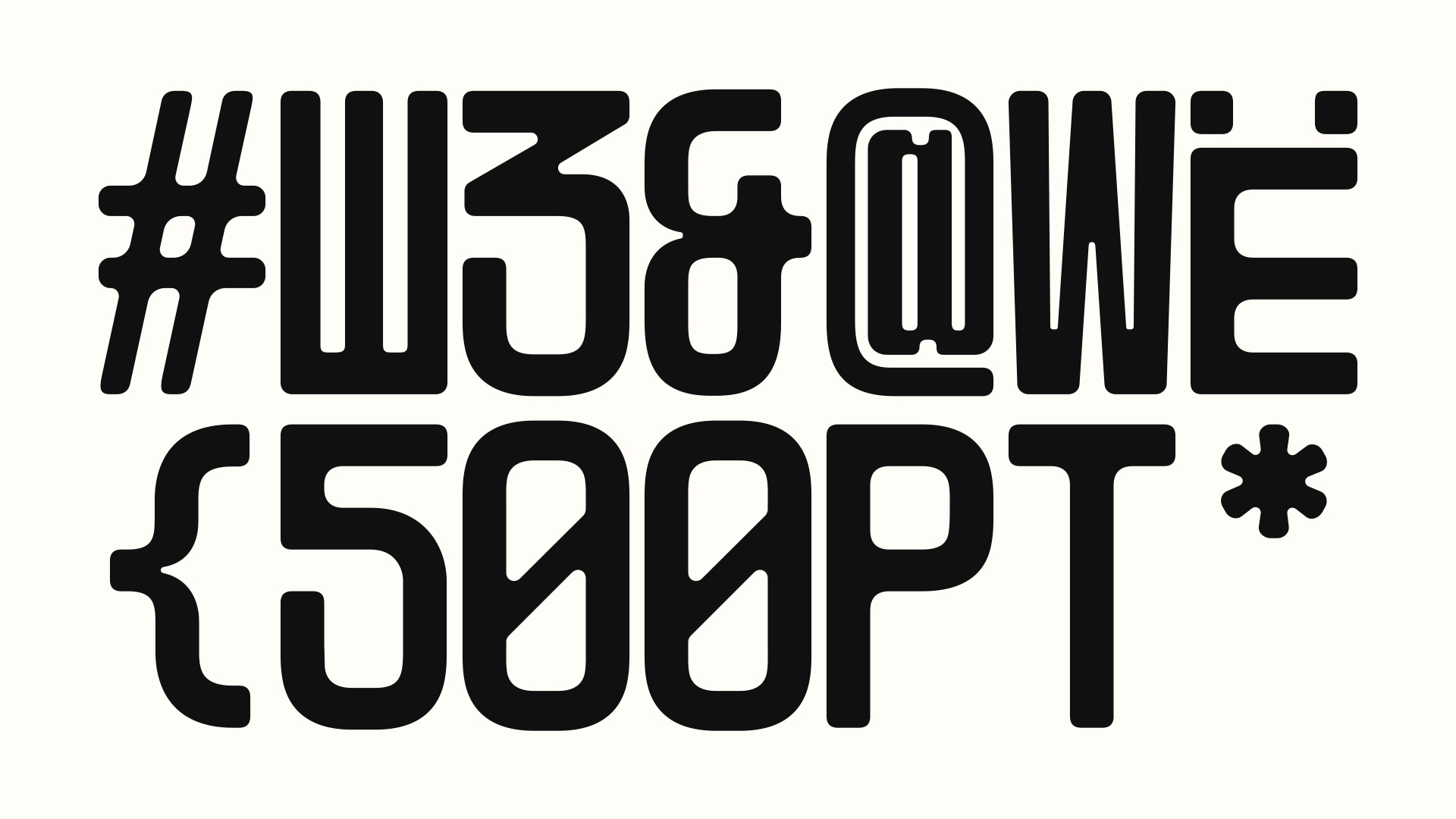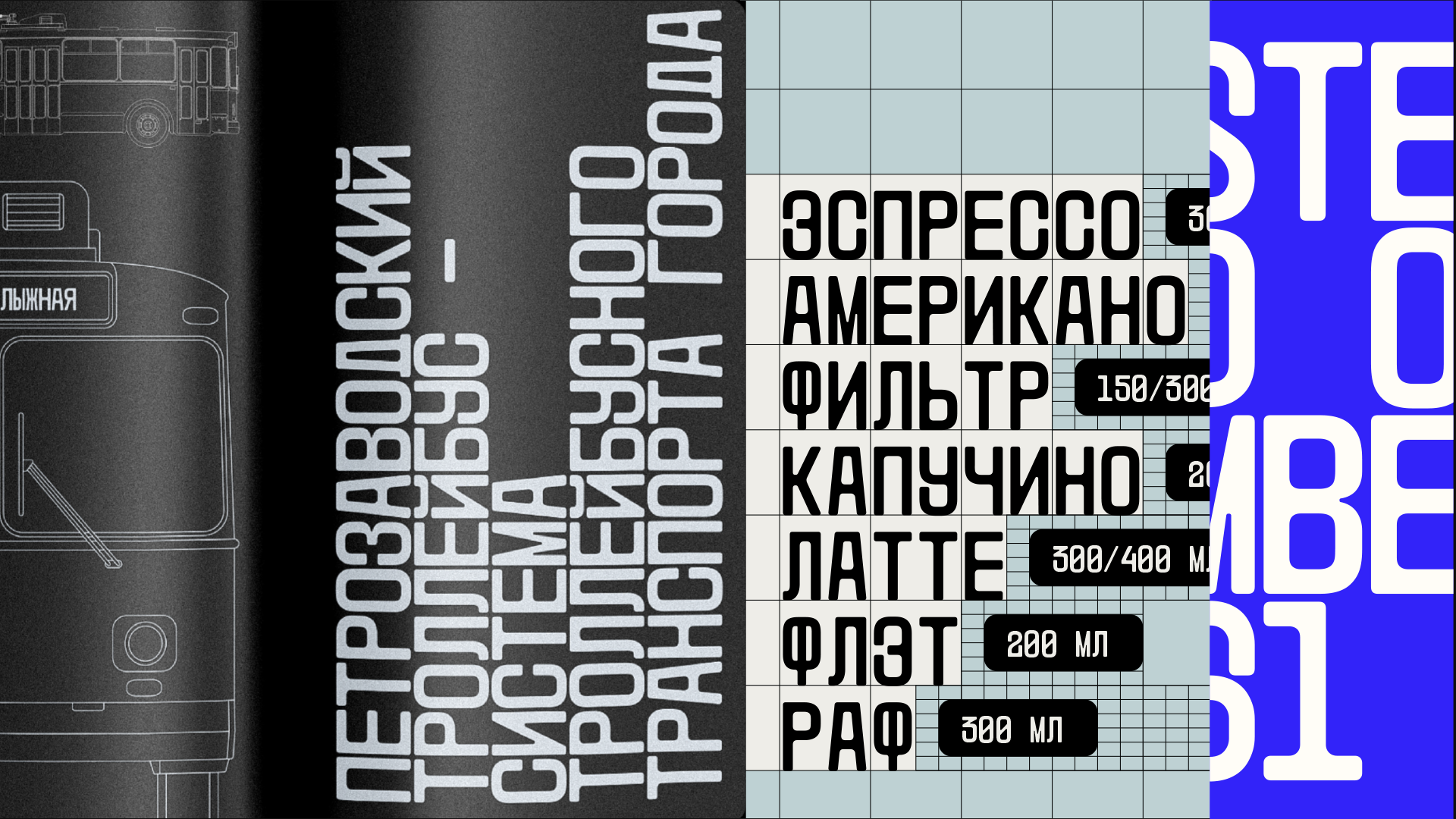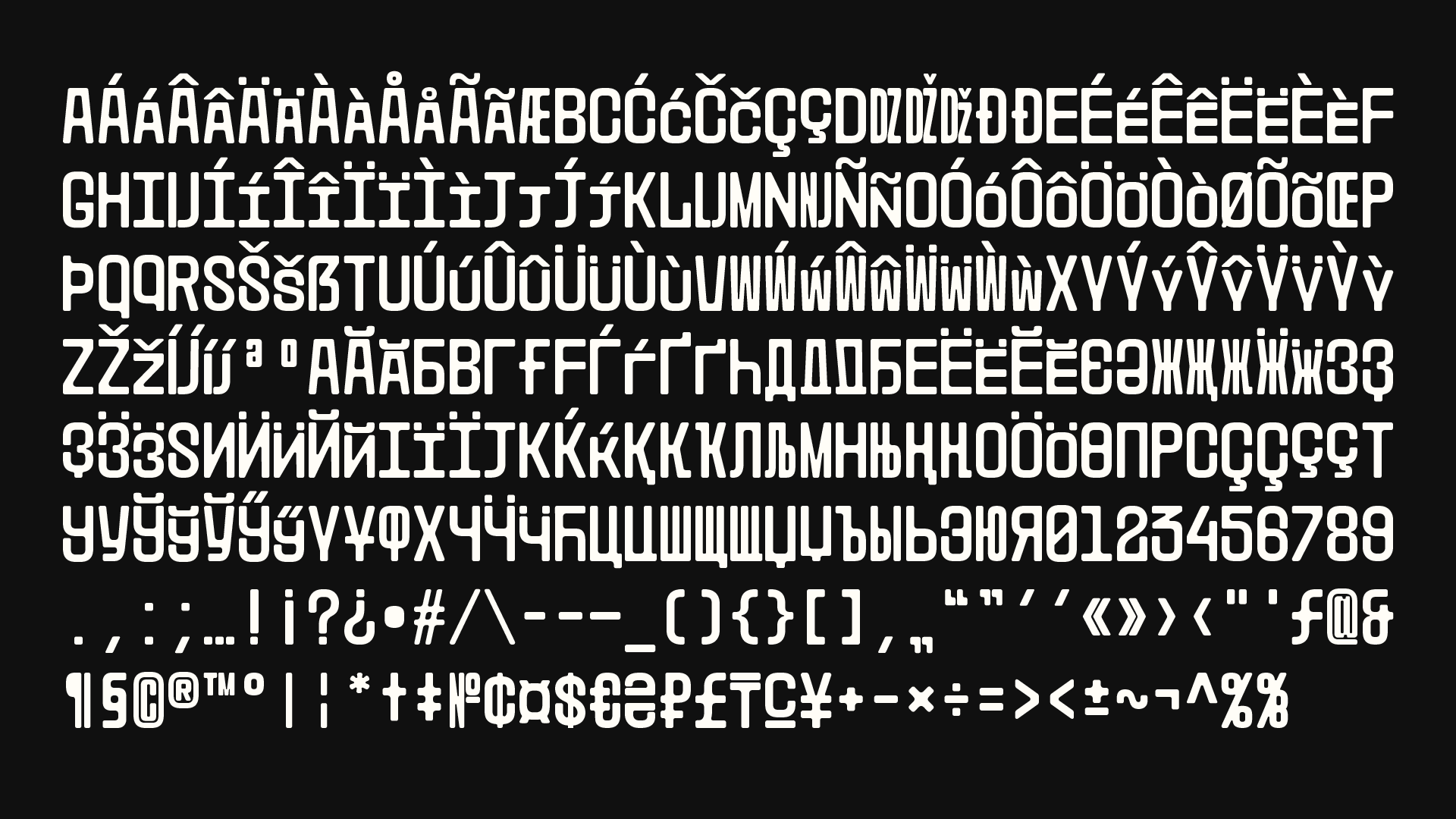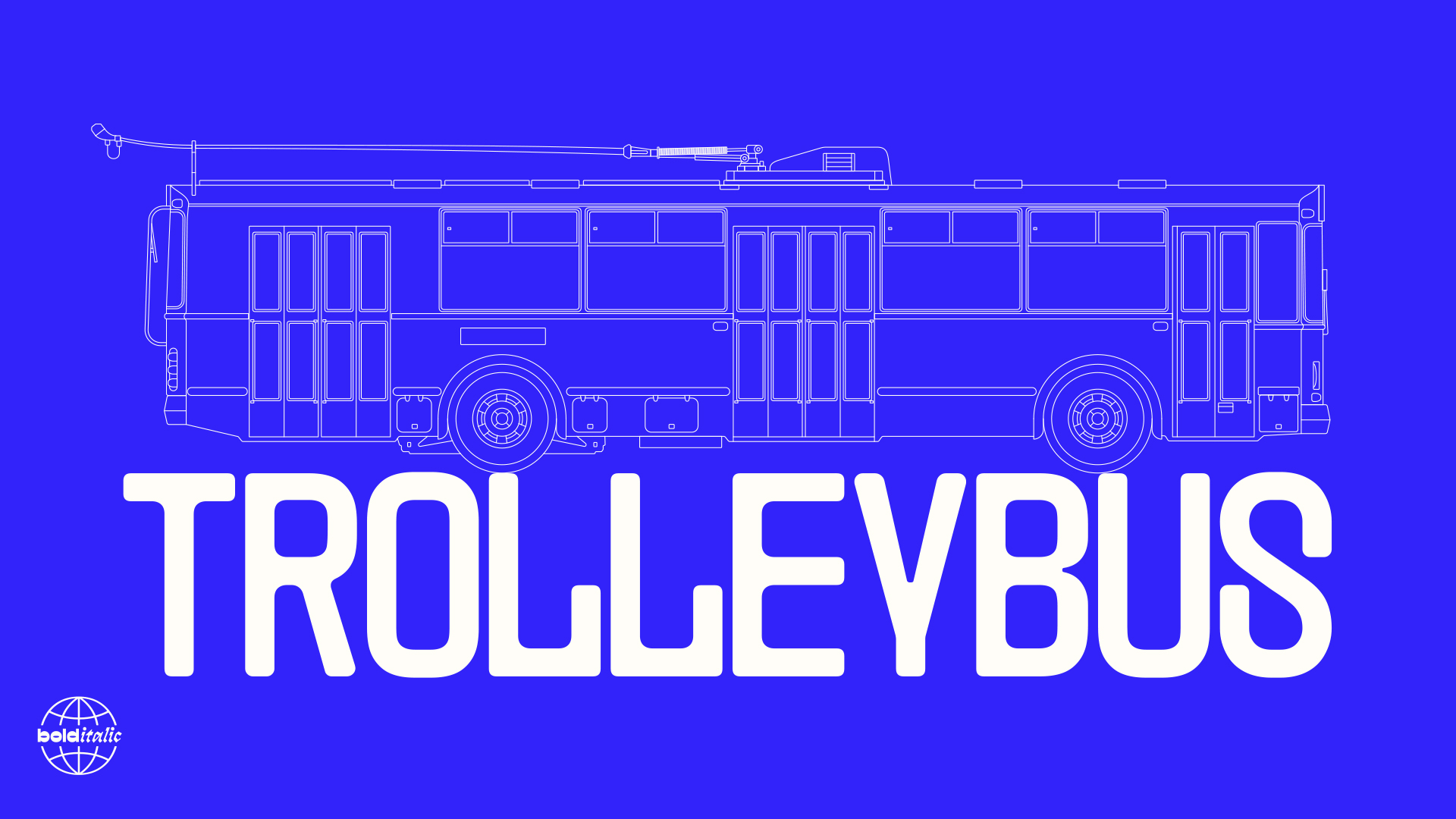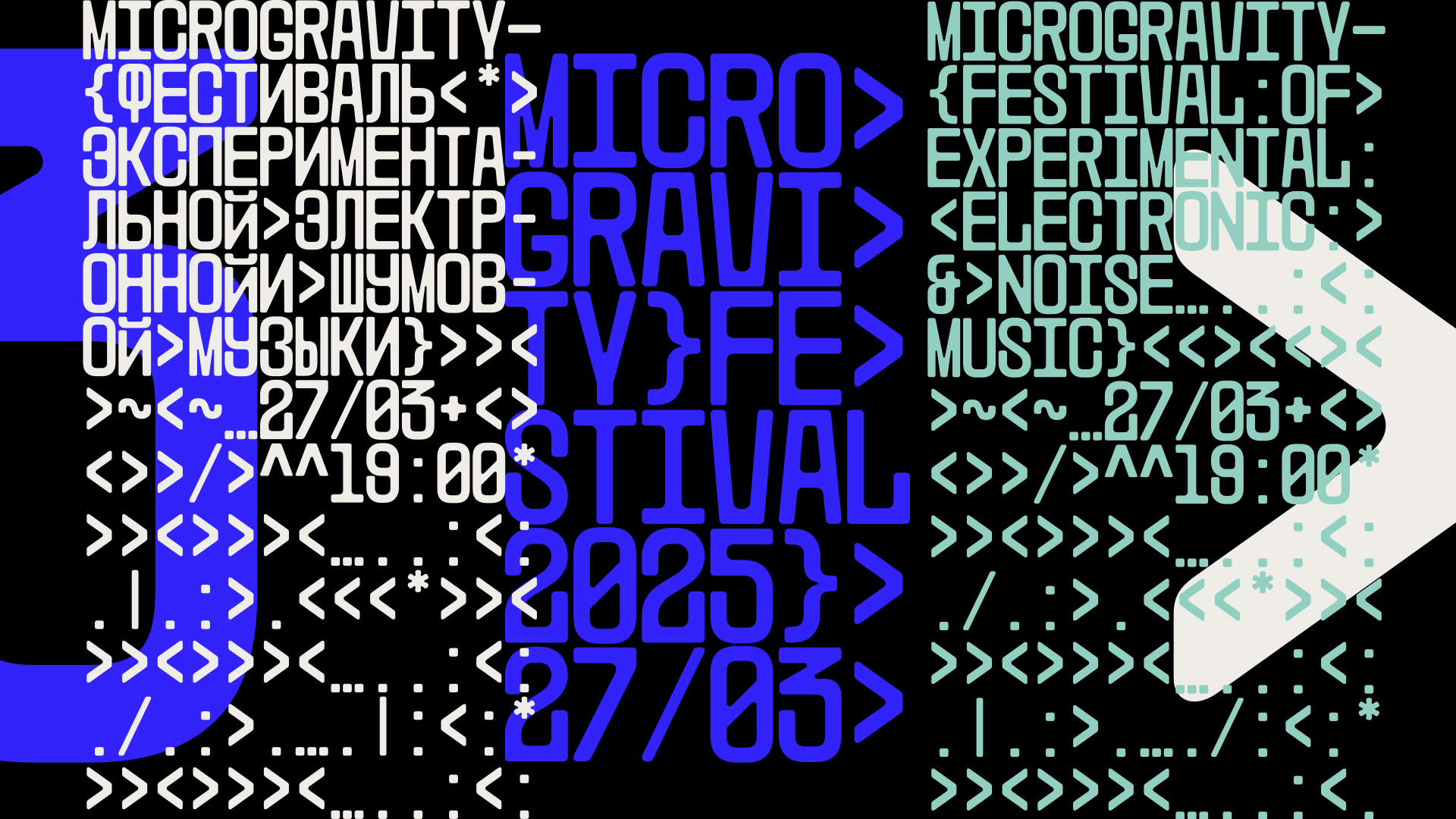
Тиражный шрифт
Trolleybus
Моноширинный акцидентный гротеск с наивно-брутальным характером. Пластические решения были вдохновлены конструктивными особенностями троллейбусов и технической типографикой. Одной из важных особенностей Trolleybus является чёткий и равномерный ритм внутри набора. Несмотря на свои характерные особенности, шрифт может решать разнообразные художественные задачи в зависимости от контекста, внутри которого он существует.
Студия Болдиталик
Саша Киселёв, Идея, шрифтовой дизайн, графический дизайн
Дмитрий Голуб, Арт-дирекшн, мастеринг